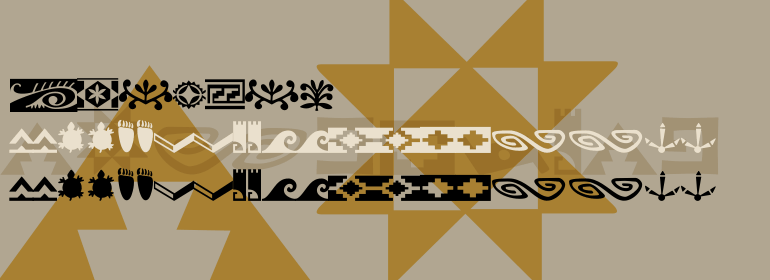
Southwest™
Southwest™,这款字体结构工整、笔画清晰,兼顾美观与易读性,适用于标题、正文、海报、包装、LOGO 等多种场景。字形优雅稳定,风格百搭耐看,适配日常排版与创意设计,让文字呈现更舒适、更具质感。Southwest™一笔一画,皆是细节,以均衡的比例、流畅的线条打造舒适视觉体验,字形端正大气,风格简约现代。无论是商业设计、品牌宣传还是日常排版,都能轻松驾驭,让文字更有格调与力量。Southwest™字体下载。